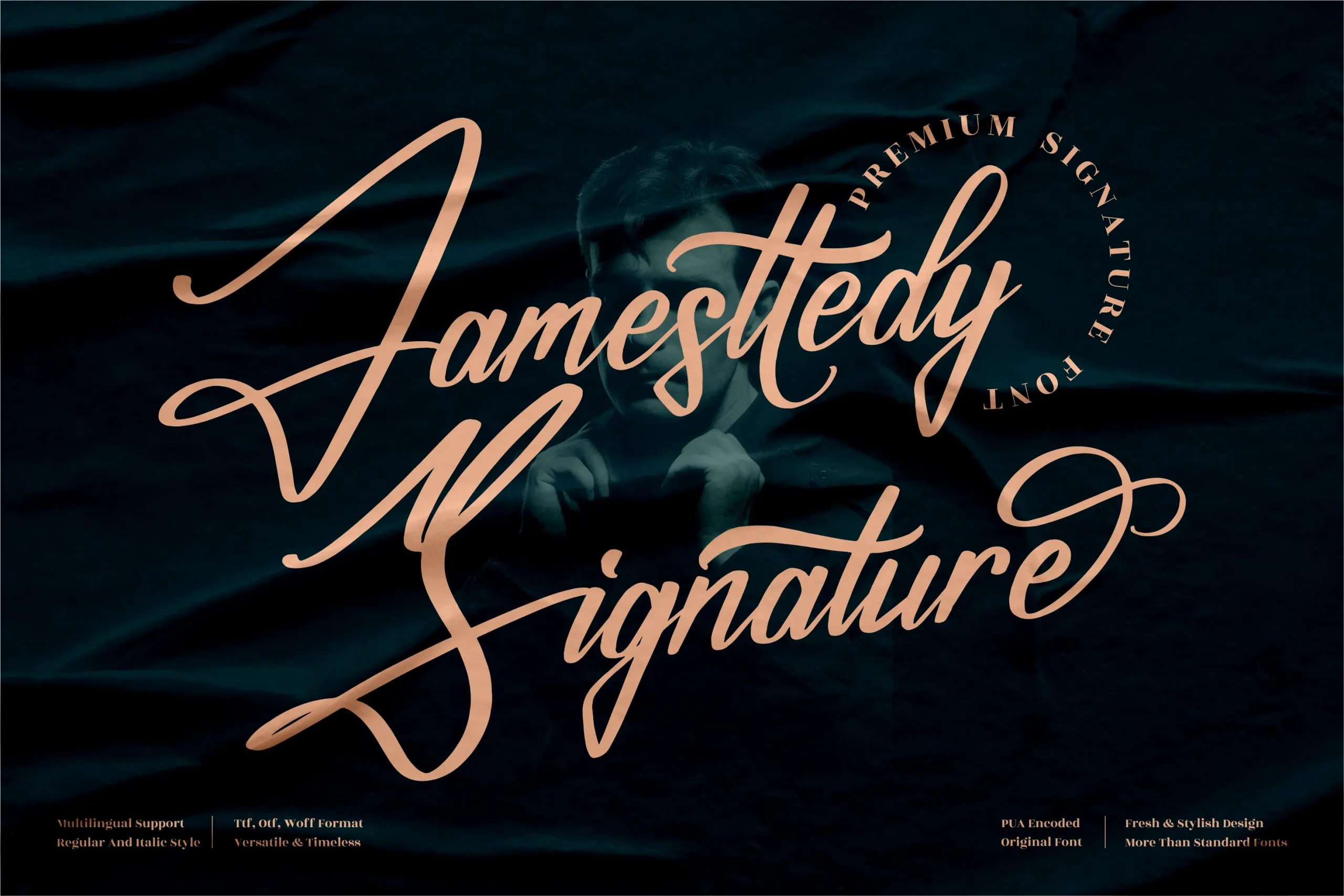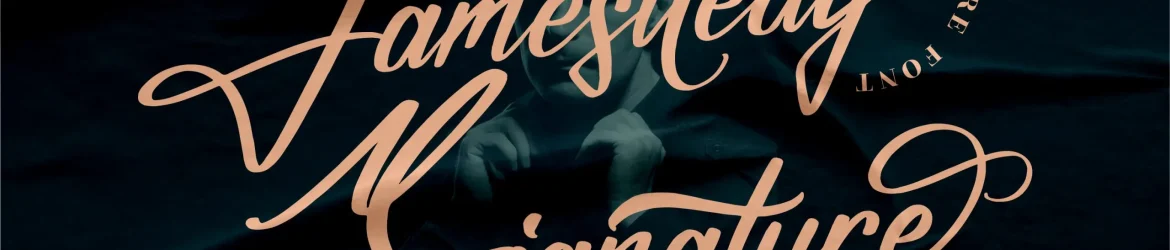
Essa é uma fonte de traço de签字,perfeita para qualquer projeto que exige um toque de elegância premium, desde logotipos e projetos de marca até embalagens de produtos, sacolas shopping e cartões de lembrança. A fonte Jamesttedy Signature é perfeita para os mais sofisticados entre vocês, seja em nome cardes, convites, cartas de boas-vindas, rótulos ou mesmo capas de livros. Com uma característica única que remete à escrita tradicional chinesa, a Jamesttedy Signature Font oferece um toque elegante e sofisticado. A sua tipografia tem um equilíbrio perfeito entre ser original e facilmente integrável em qualquer projeto, tornando-se um recurso indispensável para aqueles que desejam dar um toque diferenciado a seus projetos. Seja você um designer de logotipos ou uma marca com uma necessidade específica de design de embalagens, não há dúvidas de que essa fonte será perfeita para o seu próximo projeto. A Perspectype, detentora deste talentoso traço de签字,não se limita a projetar apenas um tipo de letra – é mais do que isso; é uma representação da arte e do design em sua essência.